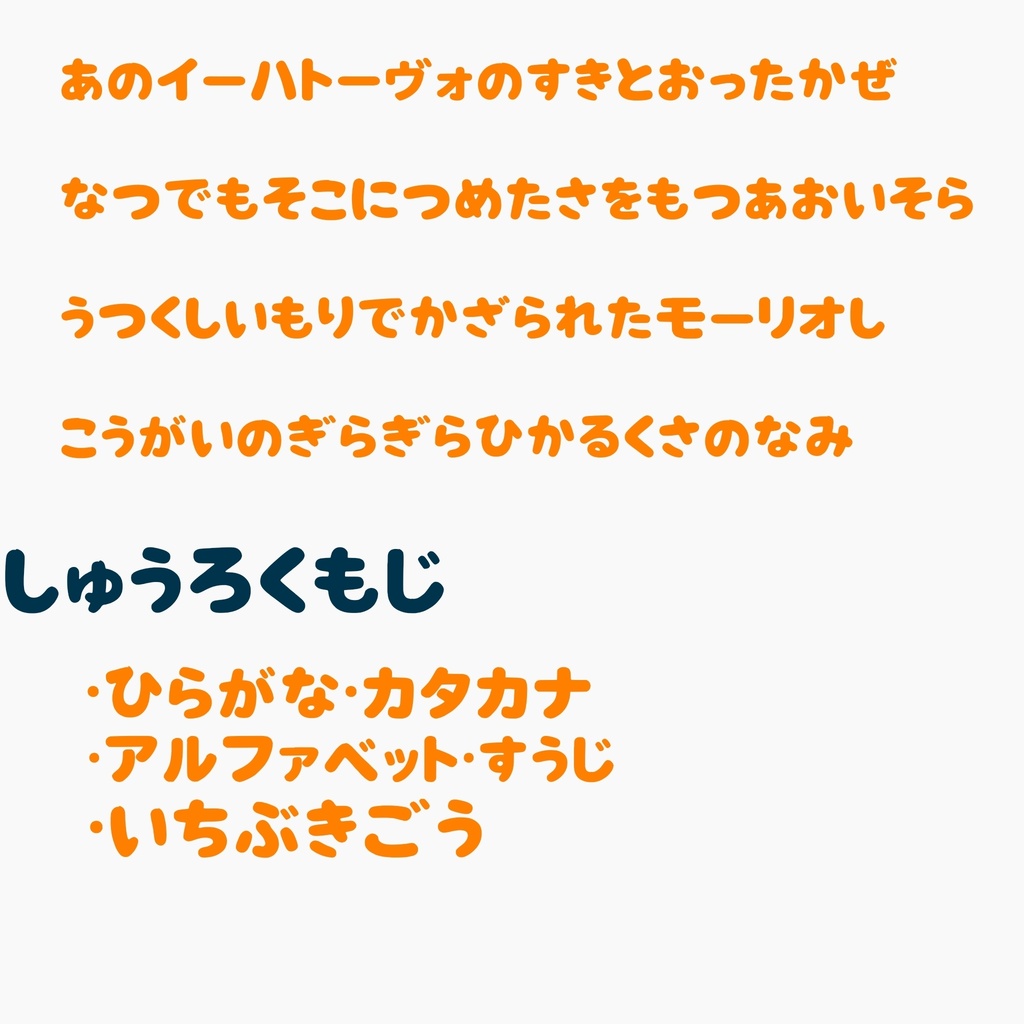
手書き風フォント「ぽっかおれんじ」
【フォントについて】 「ぽっかおれんじ」は、ひだまりのような温かさと、どこかホッとする「ゆるさ」を大切に制作した手書き風日本語フォントです。 一文字ずつ丁寧にバランスを整えつつ、カッチリしすぎない可愛らしいフォルムに仕上げました。 イラストのロゴ、ゲームのUI、動画のテロップ、SNSの画像作成など、親しみやすさを出したいシーンにぴったりです。 【収録文字】 ひらがな カタカナ アルファベット(英数字) 一部記号 ※漢字は含まれておりません。 【動作確認済み環境】 Windows 10 Android (ファイル形式:OTF / OpenTypeフォント)